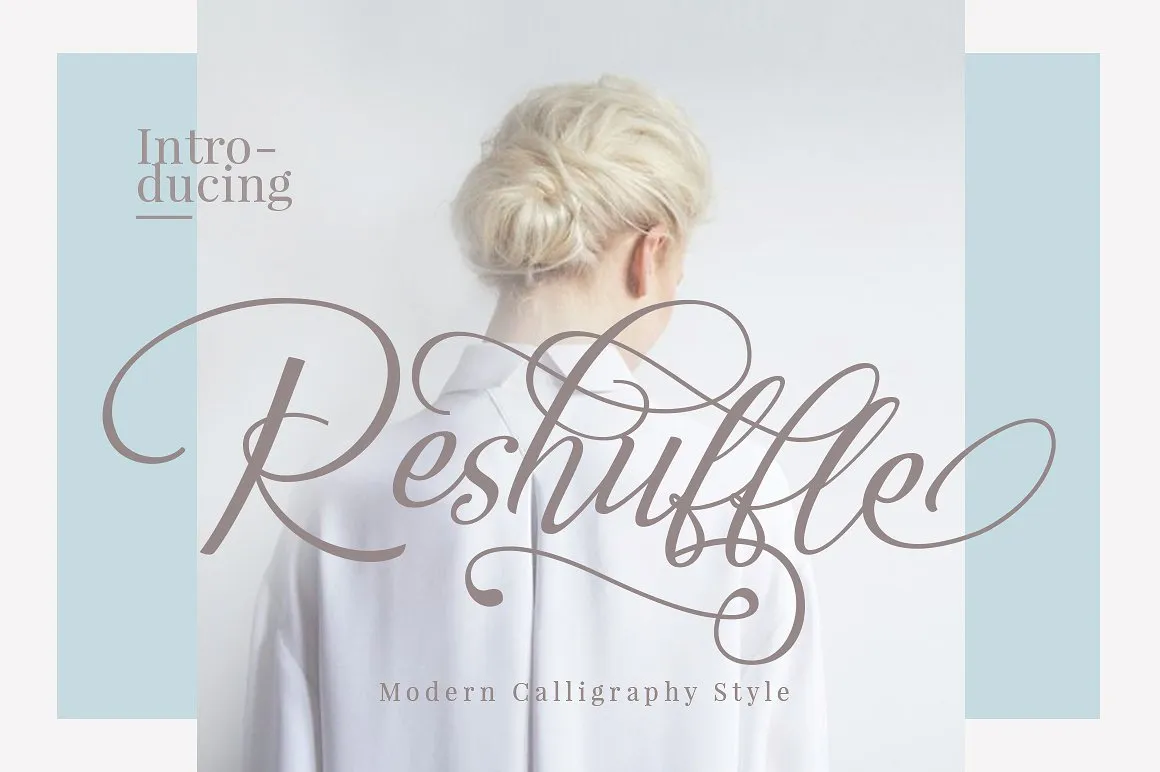
Reshuffle Script Font – Download Grátis
Introduzimos a nova fonte de script Reshuffle Script Font, criada pelo Dirtyline Studio. Este novo tipo é uma mistura fresca e moderna que traz elementos de escrita feita à mão e caracteres decorativos para um estilo elegante. A ideia do design é capturar o espírito jovial e divertido da tipografia script enquanto mantém a qualidade profissional necessária em materiais comerciais como cartões de convidado, embalagens de marca, cartões de visitas, frases motivacionais e até mesmo as propagandas. A Reshuffle Script é tão linda que parece brincar com o papel, dando um toque único para qualquer design. Ela se encaixa em uma variedade de projetos, tornando-a perfeita não apenas para cartões de convite ou mensagens pessoais, mas também para trabalhos comerciais e publicitários, garantindo que seu estilo seja notável tanto no formato tradicional quanto na nova era digital.